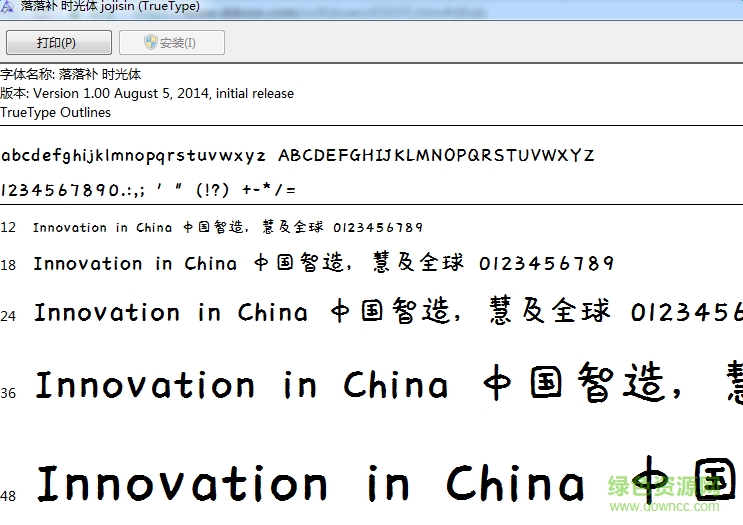
落落補(bǔ)時(shí)光體是一款超有個(gè)性的字體,該字體可以廣泛應(yīng)用于廣告設(shè)計(jì)、宣傳海報(bào)、ppt、影視制作以及任何使用文字的領(lǐng)域,有需要的朋友可以免費(fèi)下載收藏。
落落補(bǔ)時(shí)光字體是一款個(gè)性字體,該字體形體非常飄逸,字體整體效果比較出色,有喜歡的朋友可以來(lái)綠色資源網(wǎng)下載體驗(yàn)!